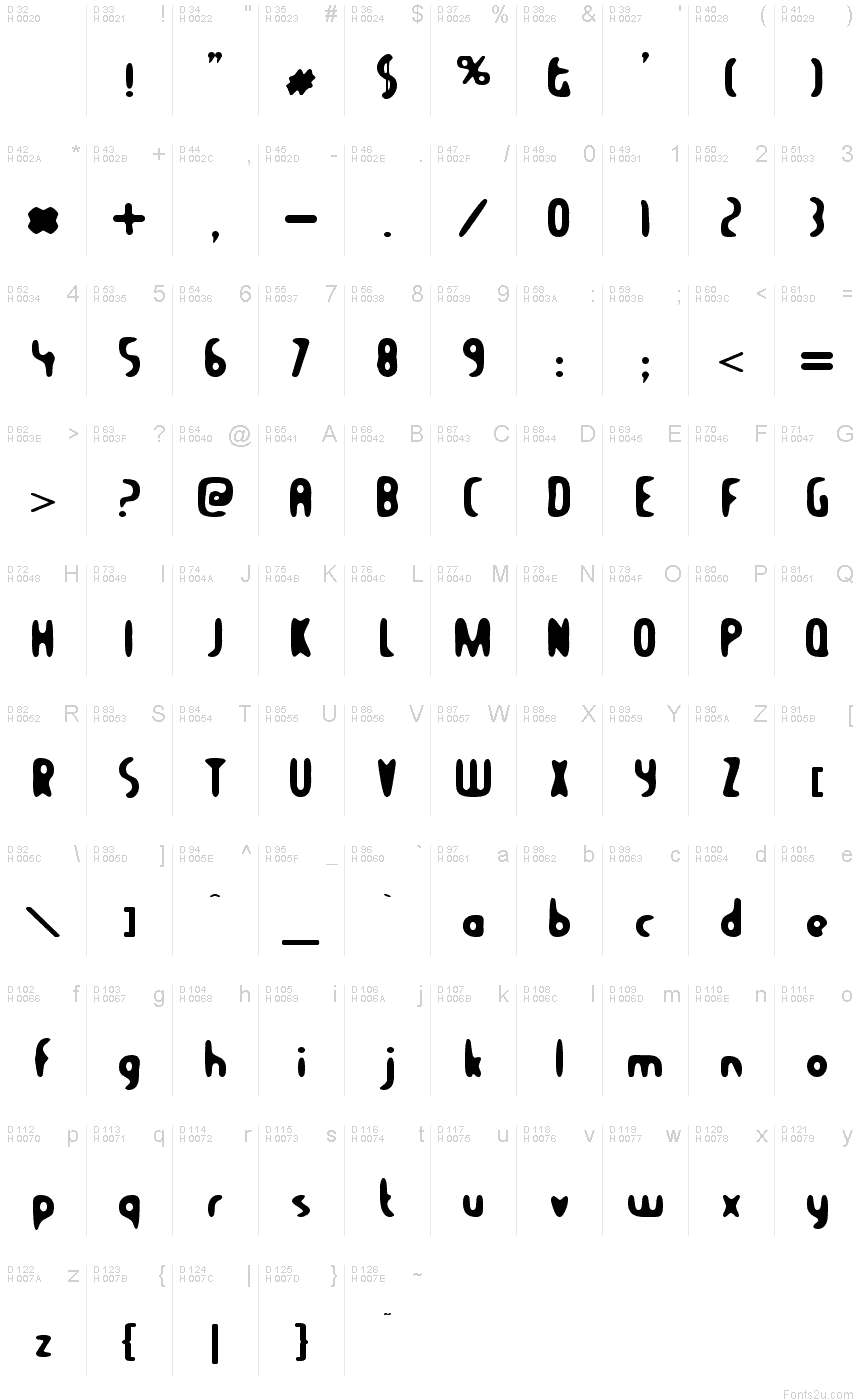
خط Balcony Angels من تصميم Ray Larabie هو خط تزييني مجاني ومرح، يتميز بضربات ناعمة وممتلئة وإيقاع يدوي متذبذب يشبه مزيجاً بين حبر القصص المصورة وختم مطاطي. تجعل الأشكال المستديرة الضخمة العناوين تبدو بارزة وودودة في آن واحد، مما يضمن بقاء النصوص المرحة واضحة دون أن تتحول إلى فوضى بصرية.
يعمل Balcony Angels بشكل رائع في ملصقات الأطفال، ومجموعات الملصقات، ودعوات الحفلات، وعلامات الحلويات التجارية، وصور مصغرة لموقع YouTube، وعناوين القصص المصورة، والرسومات التعليمية. يحتاج هذا الخط المجاني إلى القليل من المساحة؛ لذا يُنصح بدمجه مع خط بسيط بلا زوائد مثل Montserrat للنص الأساسي، حتى تظل شخصيته الناعمة والمميزة هي محور التركيز.